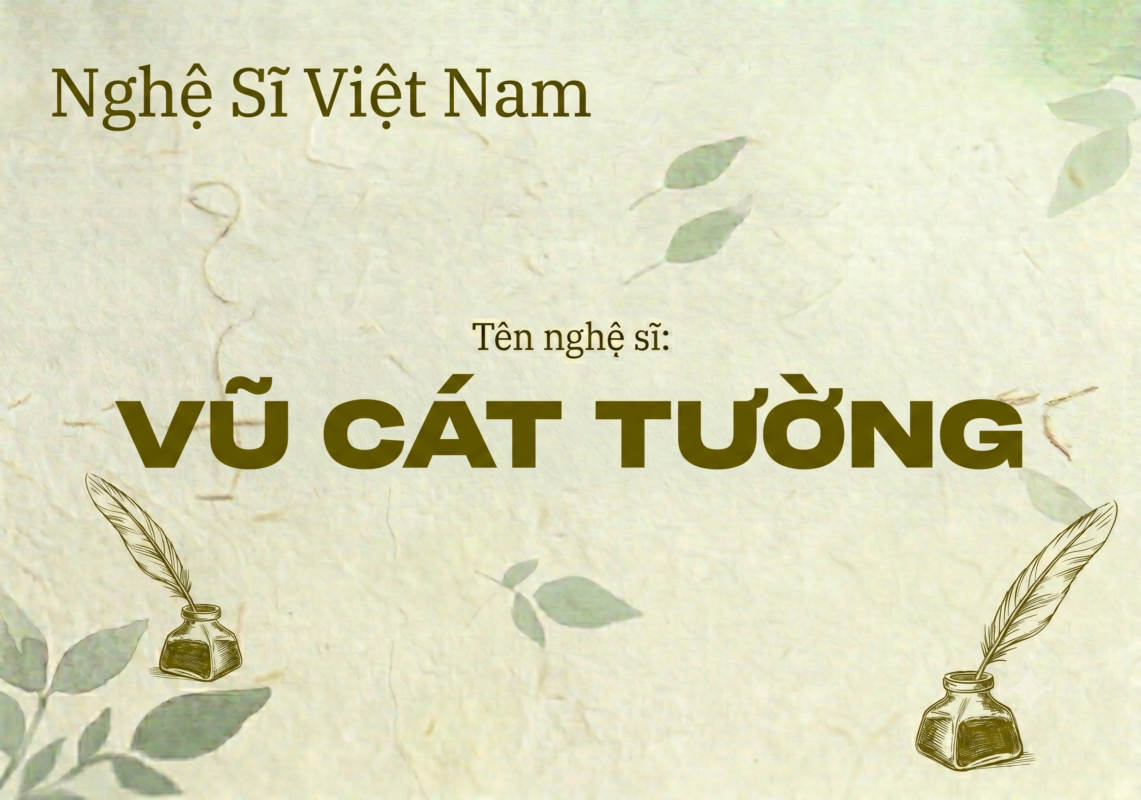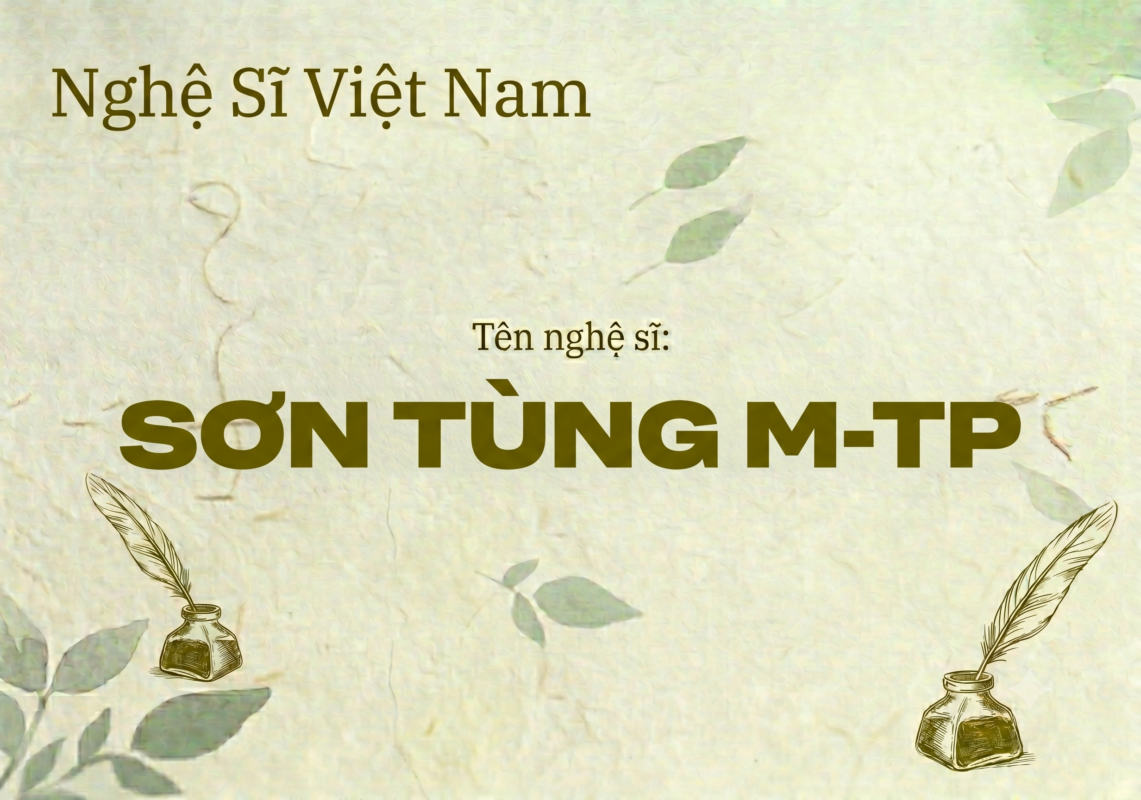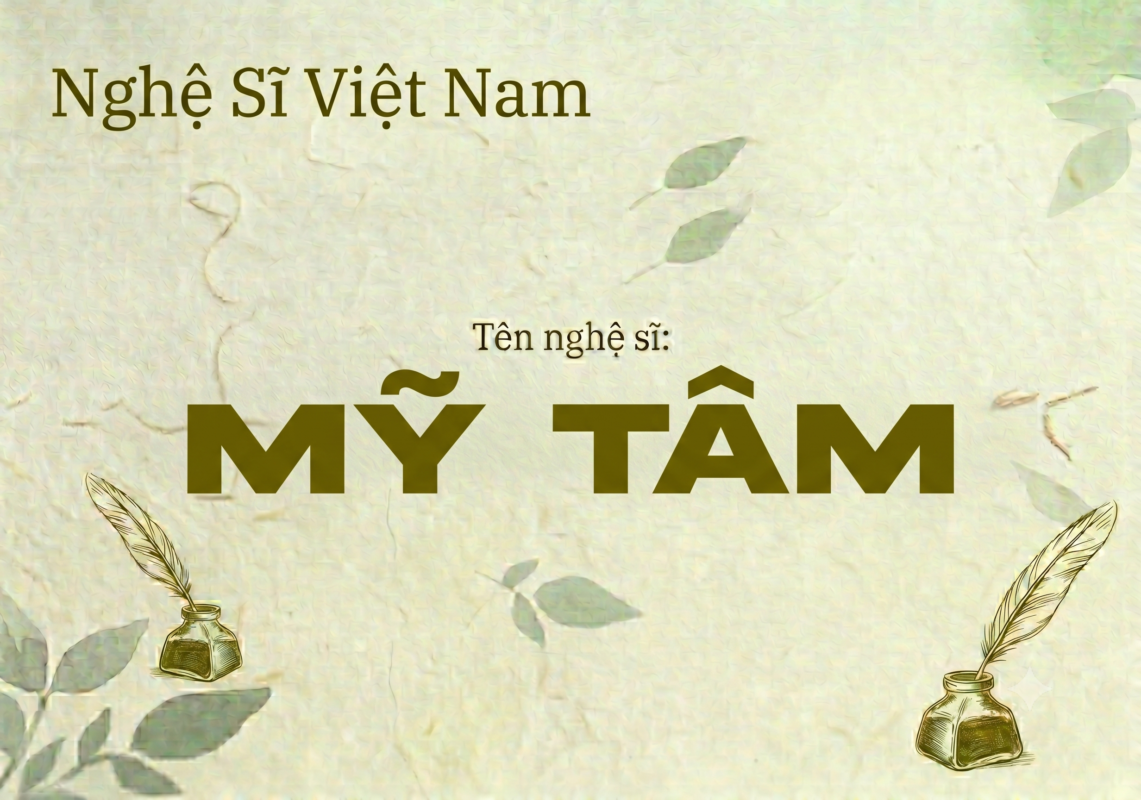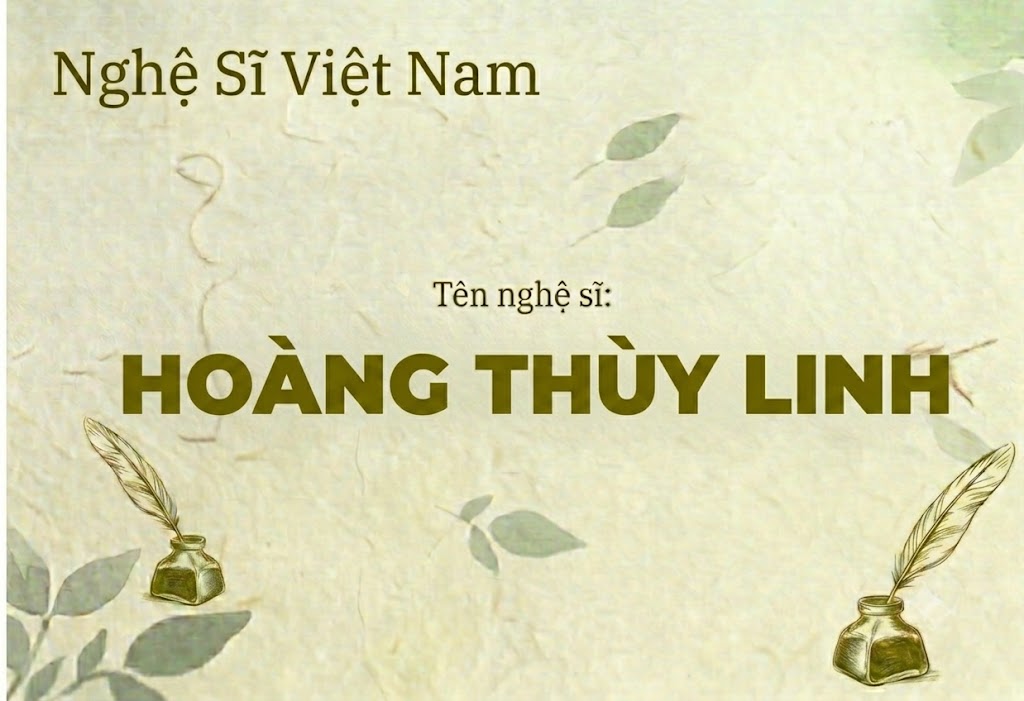
1FTV Akira Expanded
Bên cạnh những phông chữ thuôn dài hay những kiểu nét chữ dày nguyên khối thông thường, xu hướng thiết kế hiện đại luôn đánh giá cao những bộ font dạng mở rộng theo chiều ngang (expanded) đầy phá cách. Nếu bạn đang muốn tìm kiếm một giải pháp thiết kế làm tiêu đề mang lại cảm giác điện ảnh, mạnh mẽ, hầm hố và chiếm trọn không gian thị giác của người xem, thì font 1FTV Akira Expanded chính là sự lựa chọn không thể bỏ qua.
Đây là một công cụ đắc lực giúp các nhà sáng tạo nội dung, các designer định hình phong cách thiết kế có độ nhận diện cao. Phông chữ này đặc biệt phù hợp để làm các cụm chữ “giật tít” trên thumbnail Youtube, banner ngành game, thiết kế áo phông streetwear hoặc làm tiêu đề mở đầu cho các dòng video ngắn đầy năng lượng. Với phom dáng bè rộng cực kỳ cá tính, font 1FTV Akira Expanded sẽ giúp sản phẩm của bạn thu hút mọi ánh nhìn ngay từ giây đầu tiên.
Giới thiệu về font 1FTV Akira Expanded
Font 1FTV Akira Expanded là một phông chữ display (hiển thị) không chân được thiết kế với cấu trúc mở rộng chiều ngang vô cùng mạnh mẽ, hiện đại và đậm chất công nghiệp. Phiên bản này được hoàn thiện và xuất bản vào ngày 28 tháng 4 năm 2020 thông qua công cụ chuyên nghiệp FontCreator 12.0.0.2545 phiên bản 64-bit.
Sản phẩm xuất hiện trong bài viết sở hữu định dạng opentype layout hàng đầu, tích hợp chứng thực kỹ thuật số (digitally signed) cùng các đường nét đồ họa dạng postscript outlines siêu chuẩn. Nhờ những thông số kỹ thuật cao cấp này, phông chữ đảm bảo khả năng hiển thị mượt mà, sắc nét tuyệt đối, không xảy ra hiện tượng vỡ nét hay lỗi răng cưa cho dù bạn co giãn ở bất kỳ kích thước nào trên các phần mềm đồ họa hiện nay. Được chia sẻ bởi đội ngũ 1FTV, đây là một trong những bộ font mở rộng được săn đón nhất tại thị trường thiết kế Việt Nam.
Đặc điểm nổi bật của phong cách thiết kế Akira Expanded
Sức hút không thể trộn lẫn của font 1FTV Akira Expanded đến từ phom chữ siêu rộng và các đường nét dày dặn, vững chãi. Các ký tự không phát triển theo chiều cao truyền thống mà được kéo giãn sang hai bên một cách táo bạo, tạo ra một cảm giác vô cùng hoành tráng, kiên cố giống như các khối kiến trúc hiện đại hoặc các ấn phẩm truyền thông của dòng phim hành động Hollywood.
Phông chữ được xây dựng hoàn toàn theo cấu trúc all-caps (viết hoa toàn bộ), mang lại sự đồng đều tuyệt đối về mặt cao độ và khoảng cách khi bạn sắp xếp các dòng chữ cạnh nhau. Nhờ kết cấu hình khối dứt khoát và độ tương phản không gian cực mạnh, kiểu chữ này giúp phần nội dung của bạn luôn nổi bật lên hẳn, tạo ra một điểm nhấn thị giác cực lớn đè lên các chi tiết nền phức tạp phía sau.
Hệ thống khoảng cách chữ (kerning) và khoảng cách dòng (tracking) đã được xử lý chuẩn xác, giúp các ký tự khi đứng cạnh nhau không bị dính nét hay chồng chéo lên nhau dù sở hữu phom chữ bè ngang rất lớn. Bên cạnh bộ chữ cái viết hoa đồng đều, phông chữ còn đi kèm dãy số từ 0-9 và hệ thống các ký tự đặc biệt, dấu câu cơ bản (.,;:''"(!?)+-*/=), mang lại sự tiện lợi tối đa cho người sử dụng trong quá trình biên tập nội dung.
Hình ảnh demo thực tế của font 1FTV Akira Expanded
Để giúp bạn có cái nhìn trực quan nhất về độ sắc nét cũng như khả năng co giãn linh hoạt của phông chữ này trên các kích thước hiển thị, hãy cùng điểm qua bảng mô phỏng thực tế từ nhỏ đến lớn:
Kích thước nhỏ (12pt – 24pt): Các nét chữ siêu đậm và khoảng cách mở rộng vẫn giữ được sự rõ ràng, dễ đọc trên màn hình thiết bị di động.
Kích thước lớn (36pt – 72pt): Đây chính là không gian lý tưởng để font chữ phô diễn toàn bộ sức mạnh hình khối, tạo ra một hiệu ứng thị giác đè nặng cực mạnh, vô cùng thích hợp cho các tiêu đề chính.
Ứng dụng của font Akira Expanded trong thiết kế đồ họa và làm video
Sở hữu nét cá tính bứt phá và mạnh mẽ, font 1FTV Akira Expanded trở thành sự lựa chọn ưu tiên cho rất nhiều dự án truyền thông, marketing thế hệ mới:
Thiết kế thumbnail Youtube và ảnh thu nhỏ mạng xã hội: Đây là vũ khí cực mạnh để tăng tỷ lệ nhấp chuột (CTR). Khi bạn kết hợp các khối chữ Akira Expanded với tông màu nổi bật như vàng, trắng, đỏ trên các phần nền tối, dòng chữ tiêu đề sẽ ngay lập tức đập vào mắt người xem.
Làm tiêu đề video ngắn (Tiktok, Shorts, Reels): Kiểu chữ mở rộng này rất thích hợp để làm các cụm từ từ khóa chính, tiêu đề mở đầu video hay phụ đề phong cách ngầu, giúp giữ chân người xem lướt chậm lại.
Banner và poster thể thao, gaming: Hoàn hảo cho các poster giải đấu thể thao điện tử (esports), banner câu lạc bộ gym, fitness, xe độ hoặc các sự kiện hành động đòi hỏi tính cơ bắp và năng động.
Nhận diện thương hiệu thời trang streetwear: Phù hợp làm logo dạng chữ khối, artwork in lên áo phông, áo hoodie cho các thương hiệu thời trang mang phong cách đường phố, bụi bặm và phá cách.